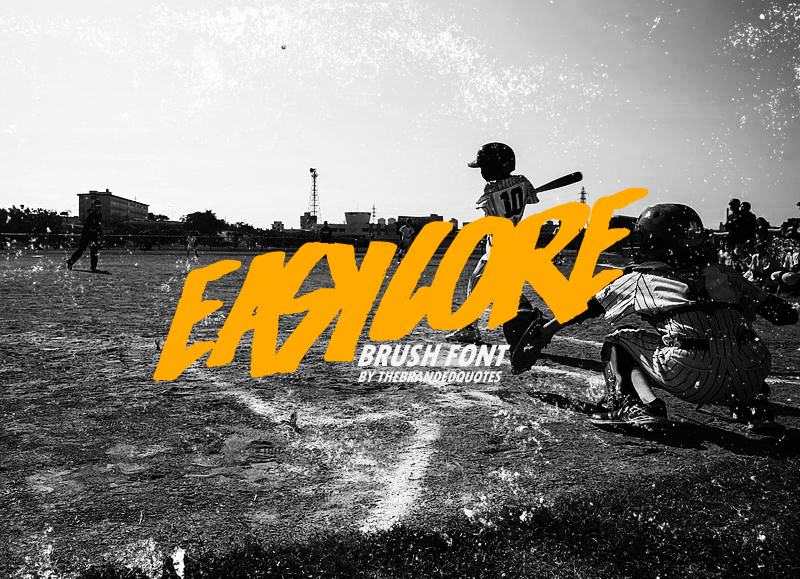
Easycore Brush Font – Fonte Grátis
Easycore Brush Font
A Easycore Brush Font é uma versão perfeita para os designers que buscam um estilo elegante e sofisticado na criação de materiais digitais. Criada pelo designer thebrandedquotes, esta fonte script foi concebida para oferecer um toque autêntico e desenho às suas produções. Em sua versão personal uso exclusivo, a Easycore Brush Font é ideal para projetos pessoais e de design gráfico que não requerem fins comerciais. Para adquirir a versão comercial com todas as permissões, basta clicar aqui: https://sellfy.com/p/2ORx/. Esta fonte se destaca por suas linhas fluidas e delicadas, fornecendo aos criadores uma ferramenta poderosa para expressar seu trabalho de forma única. Se você está procurando por um recurso gráfico versátil que pode aprimorar seus projetos digitais sem comprometer a qualidade do design, a Easycore Brush Font é definitivamente o item perfeito na sua carteira de recursos.